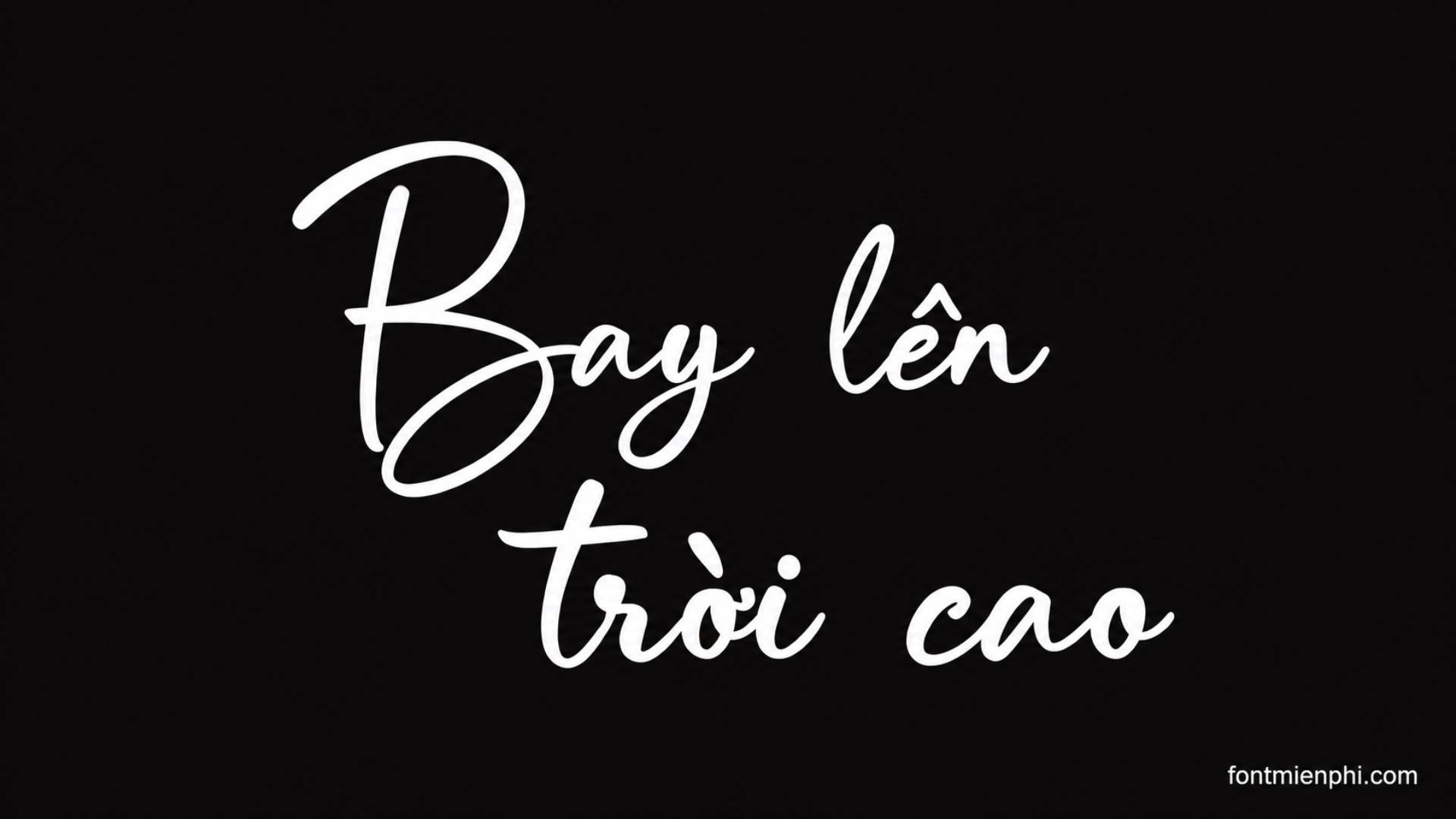
Font Việt hóa 1FTV VIP Hiragenda
Bạn đang tìm kiếm một làn gió mới cho các dự án thiết kế mang phong cách high-fashion, sang trọng hay các ấn phẩm truyền thông đòi hỏi tính nghệ thuật cao? Font Việt hóa 1FTV VIP Hiragenda chính là siêu phẩm tiếp theo bạn phải thêm ngay vào kho tài nguyên của mình. Thuộc phân khúc font VIP cao cấp, Hiragenda mang đến một diện mạo đầy mê hoặc, giúp nâng tầm mọi tác phẩm đồ họa từ bình thường trở nên đẳng cấp.
1. Tổng quan về Font 1FTV VIP Hiragenda
1FTV VIP Hiragenda là một phông chữ được tạo ra hướng tới sự duy mỹ, thanh lịch và tinh tế. Tên gọi “Hiragenda” gợi lên sự kết hợp giữa cấu trúc hình học hiện đại và những đường cong nghệ thuật mềm mại, uyển chuyển. Font chữ này sở hữu các nét thanh đậm có sự tương phản rõ rệt, tạo nên một nhịp điệu thị giác rất lôi cuốn và thời thượng.
Nhận thấy tiềm năng ứng dụng cực lớn của bộ chữ này, đội ngũ 1FTV đã tiến hành Việt hóa một cách công phu. Toàn bộ các ký tự có dấu trong tiếng Việt đã được tinh chỉnh tỉ mỉ để giữ nguyên form dáng thanh thoát ban đầu của tác giả gốc, giúp các nhà thiết kế Việt thỏa sức sáng tạo mà không gặp bất kỳ trở ngại nào về lỗi hiển thị.
2. Những ưu điểm nổi bật của Font Hiragenda Việt Hóa
Không chỉ dừng lại ở một phông chữ đẹp, 1FTV VIP Hiragenda còn chinh phục các designer khó tính nhờ những điểm cộng vượt trội:
• Phong cách mang đậm tính thời trang (High-Fashion Vibe): Rất phù hợp với xu hướng thiết kế tối giản nhưng sang trọng (Quiet Luxury) đang thịnh hành trên toàn cầu.
• Hệ thống dấu Tiếng Việt hoàn hảo: Khoảng cách (kerning) giữa chữ và các dấu thanh (sắc, huyền, hỏi, ngã, nặng) được căn chỉnh thủ công rất kỹ lưỡng, không bị dính chữ hay rời rạc, đảm bảo tính thẩm mỹ cao nhất khi gõ văn bản.
• Bộ ký tự mở rộng phong phú (Ligatures & Alternates): Font hỗ trợ nhiều ký tự thay thế đặc biệt và các nét nối chữ nghệ thuật, cho phép bạn tự do biến tấu tiêu đề theo phong cách riêng độc đáo.
• Độ sắc nét tối ưu: Hiển thị mượt mà trên các chất liệu in ấn cao cấp cũng như các màn hình kỹ thuật số độ phân giải cao.
3. Ứng dụng thực tế của Font 1FTV VIP Hiragenda trong thiết kế
Với vẻ đẹp kiêu sa và đầy tính nghệ thuật, PS 1FTV VIP Hiragenda là vũ khí tối thượng cho các dự án:
Gợi ý phối Font (Typography Tip): Hãy sử dụng 1FTV VIP Hiragenda ở kích thước lớn cho các tiêu đề chính (Heading 1). Sau đó, kết hợp với một font Sans-serif tối giản, thanh mảnh (như Montserrat hoặc Inter) cho phần nội dung (Body text) để tạo nên sự cân bằng và phân cấp thông tin hoàn hảo.
• Thiết kế Bìa Tạp chí & Editorial: Mang lại cảm giác chuyên nghiệp, cao cấp giống như các tạp chí thời trang danh tiếng (Vogue, Harper’s Bazaar).
• Nhận diện thương hiệu (Branding & Logo): Thích hợp làm logo, slogan cho các thương hiệu mỹ phẩm cao cấp, nước hoa, trang sức, spa, hoặc các nhãn hàng thời trang thiết kế.
• Ấn phẩm sự kiện sang trọng: Thiết kế thiệp mời sự kiện, menu nhà hàng 5 sao, thiệp cưới phong cách hoàng gia.
• Bao bì sản phẩm (Packaging): Tăng giá trị định vị cho các dòng sản phẩm cao cấp, sản phẩm giới hạn (Limited Edition).